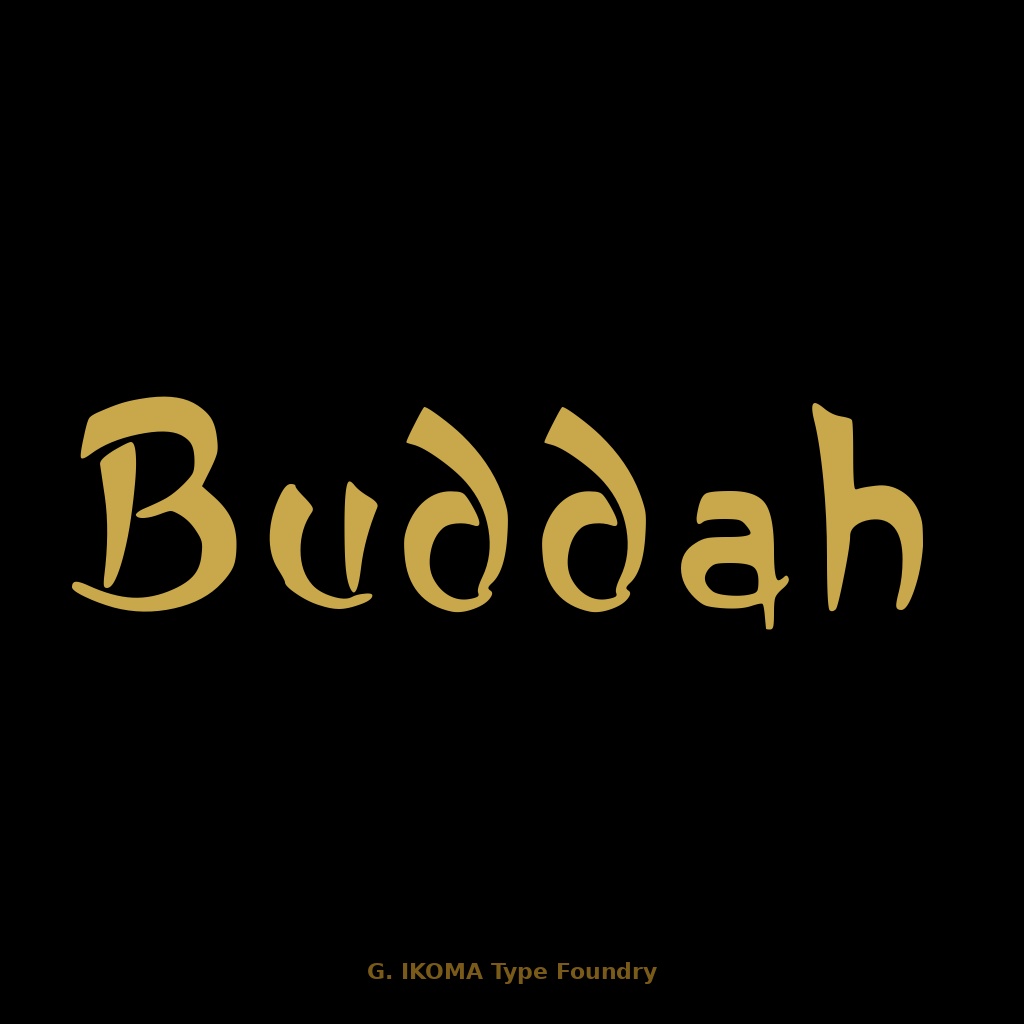
Buddah — オリジナルデザイン欧文フォント [Ethnic Decorative / Handcrafted]
━━━━━━━━━━━━━━━━━━━━━━━━━ 【フォントについて】 ━━━━━━━━━━━━━━━━━━━━━━━━━ Buddah Extended は、民族的・呪術的なエッセンスを取り込んだオリジナルデザイン欧文フォントです。 有機的で不規則なストロークが生み出す独特のリズムは、ロゴやブランド名に強烈な個性を与えます。 アルファベット大文字・小文字を収録し、原典にない記号類は一部補填していますが数字は用意されていません。 様式:Ethnic Decorative / Handcrafted 収録グリフ:126文字(大文字A-Z・小文字a-z・記号類) 欠落グリフ:数字 0〜9 ★ 制作:株式会社生駒時計店 / G. IKOMA, LTD. ━━━━━━━━━━━━━━━━━━━━━━━━━ 【ご購入前にご確認ください】 ━━━━━━━━━━━━━━━━━━━━━━━━━ 本フォントは数字(0〜9)を収録していません。 価格・年号・電話番号など、数字が必要な表現には別フォントとの組み合わせが必要です。 有機的な手書き風の字形を特徴とするディスプレイ向け書体です。 ロゴ・見出し・装飾用途には力強い存在感を発揮しますが、 本文組版や小サイズでの長文には向きません。 ━━━━━━━━━━━━━━━━━━━━━━━━━ 【収録内容】 ━━━━━━━━━━━━━━━━━━━━━━━━━ ・I_Buddah_Extended.ttf ・LICENSE.txt(日英) ━━━━━━━━━━━━━━━━━━━━━━━━━ 【推奨用途】 ━━━━━━━━━━━━━━━━━━━━━━━━━ ・ロゴ ・ブランド名 ・バンド名・アーティスト名 ・ゲームタイトル・ファンタジー系コンテンツ ・アパレルプリント ・サイン・看板 ・SNSアイコン・ヘッダー ・Tシャツ・グッズデザイン 民族的・呪術的・ファンタジー系のビジュアル表現に特に適しています。 本文組版・小サイズでの常用には向きません。 ━━━━━━━━━━━━━━━━━━━━━━━━━ 【ライセンス】 ━━━━━━━━━━━━━━━━━━━━━━━━━ 本フォントは、個人利用・商用利用を問わず、印刷物、画像、ロゴ、バナー、 動画サムネイル等の制作に使用できます。 また、WebサイトやSNSで画像化された状態で使用することは可能です。 ただし、以下の行為は禁止します。 ・フォントファイルそのものの再配布、再販売、譲渡、共有 ・改変したフォントファイルの配布 ・本フォントを素材集、テンプレート、デジタル商品等に収録して再販売する行為 ・本フォントファイルをWebフォントとしてサーバーに設置・配信して利用する行為 ・アプリケーション、ゲーム、ソフトウェア、電子機器等への埋め込み利用 ・AI学習、機械学習、生成モデル訓練等への利用 ・本フォント自体または収録字形そのものについて独占的権利を主張する行為 詳細は同梱の LICENSE.txt をご確認ください。 ━━━━━━━━━━━━━━━━━━━━━━━━━ BOOTH: https://g-ikoma.booth.pm/